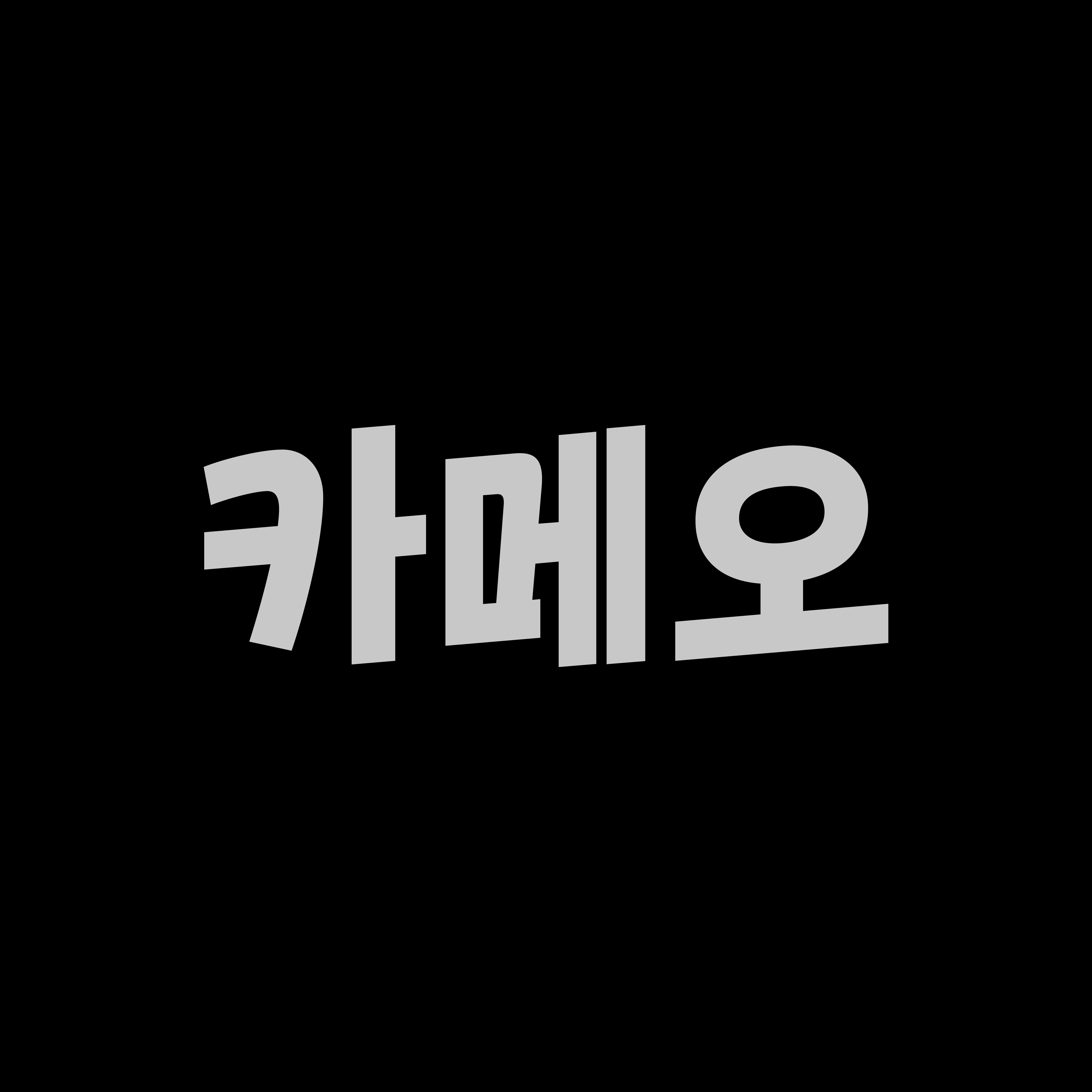
Sandoll 카메오
카메오는 영화나 드라마에서 관객의 시선을 단번에 끌 수 있는 단역 출연자를 일컫습니다. 이름처럼 산돌 카메오는 지면의 작은 부분에 사용되어도 시선을 사로잡는 폰트가 되기를 바랍니다.
산돌 카메오는 영상 매체의 자막 용도로 고안된 폰트입니다. 우상향하는 기울기가 특징적이며 영상 매체의 검은 화면에서도 선명하게 보일 수 있도록 두껍고 단단하게 설계되었습니다. 자연스러운 쓰기 방식을 따르는 휴머니스트 산스 계열의 폰트이며, 이로 인해 ‘ㄹ, ㅌ’이나 ‘ㅅ, ㅈ, ㅊ’과 같은 자소에서 캐주얼함이 묻어납니다. 기울기로 인한 리듬감만을 강조하기 위해 휴머니스트 산스의 범위 안에서 최대한 자소를 꽉 차게 설계하여 자칫 과하게 보일 수 있는 단차를 줄이려 하였습니다.